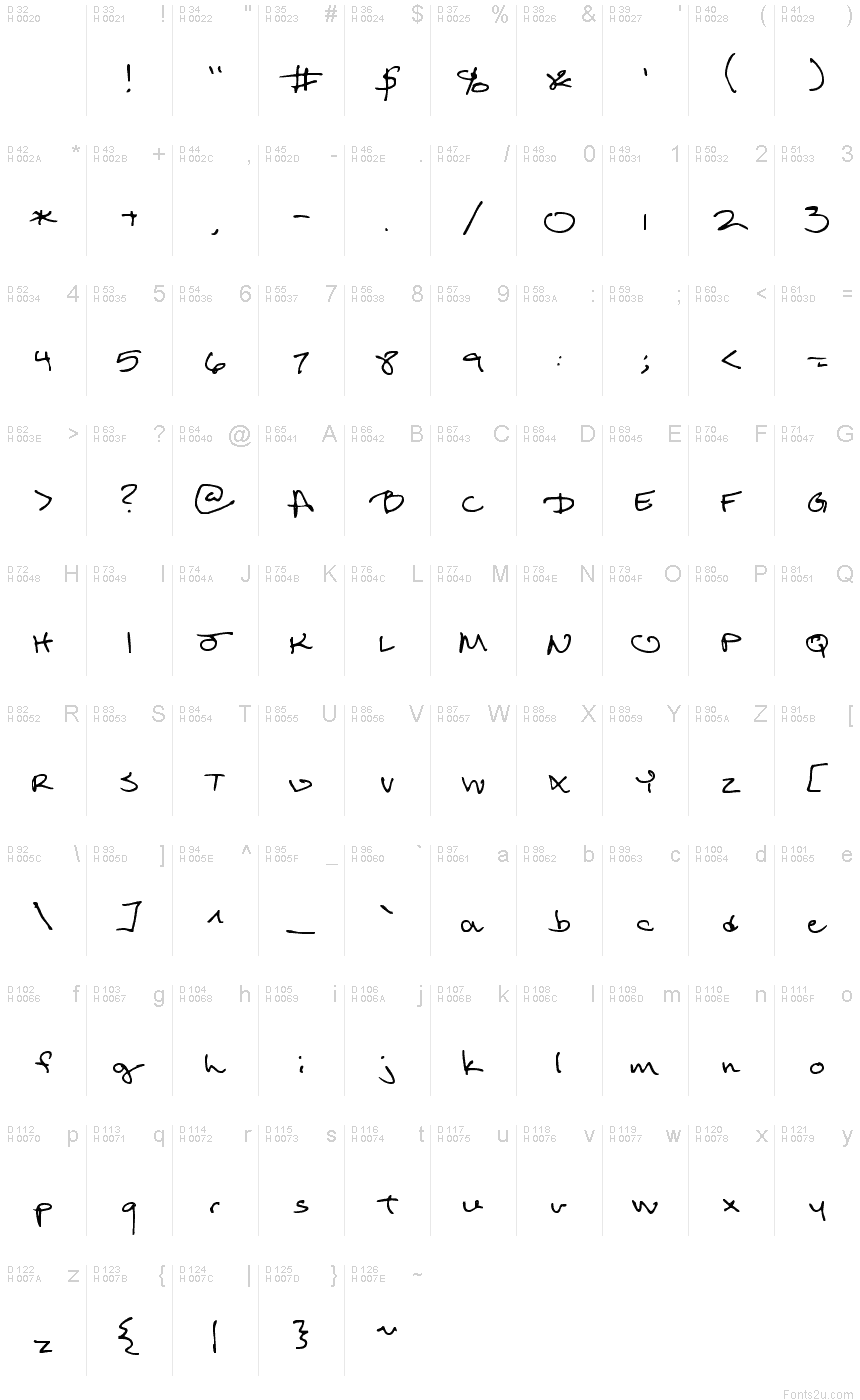
Return of RelayScript od Kreative Korporation to darmowy krój pisma typu script, który oddaje luźną, odręczną energię szybkich notatek na skrawku papieru. Litery lekko drżą i łączą się w swobodnych pociągnięciach, nadając każdemu słowu niezobowiązujący, ludzki charakter, przy zachowaniu zaskakującej czytelności w mniejszych rozmiarach. To rodzaj pisma, który sprawia wrażenie nieoszlifowanego w najlepszym tego słowa znaczeniu – jest organiczny, żywy i odrobinę szalony, dzięki czemu Twoje projekty nigdy nie wyglądają sztywno czy przekombinowanie.
Korzystając z Return of RelayScript, dodasz osobistego, spontanicznego wyrazu grafikom w social mediach, zinom, nagłówkom na blogach, etykietom produktów handmade czy postom z cytatami. Ten darmowy font błyszczy, gdy chcesz, aby tekst był naturalny i konwersacyjny, a nie korporacyjny. Połącz go z czystym, geometrycznym krojem bezszeryfowym w tekście głównym, a Return of RelayScript niech zajmie się śmiałymi nagłówkami lub krótkimi podpisami.